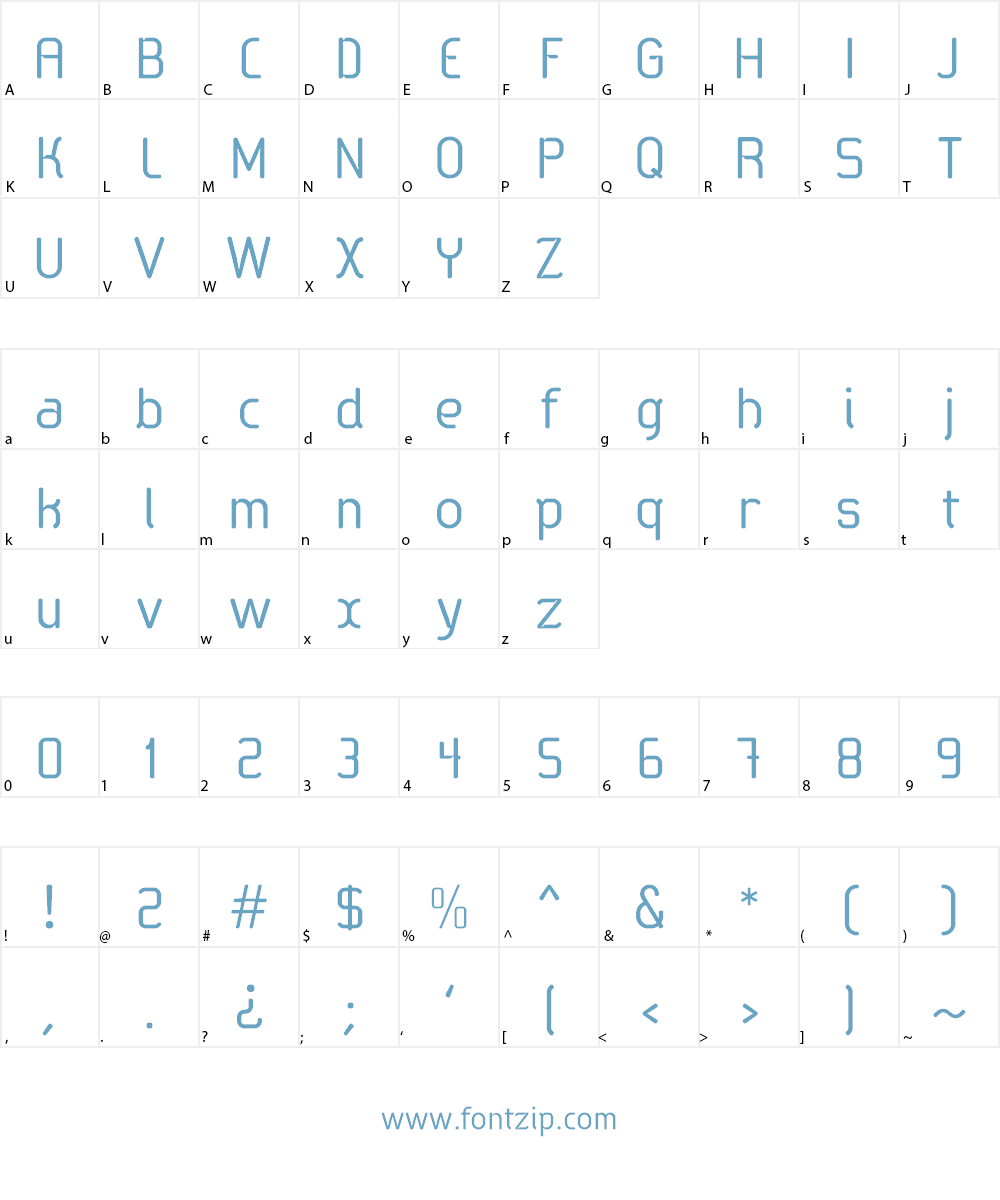
Sabática es una tipografía fruto de un sábado sin nada que hacer. Dispone de todos los idiomas européos basados en el latín. Visita mi web defharo.com